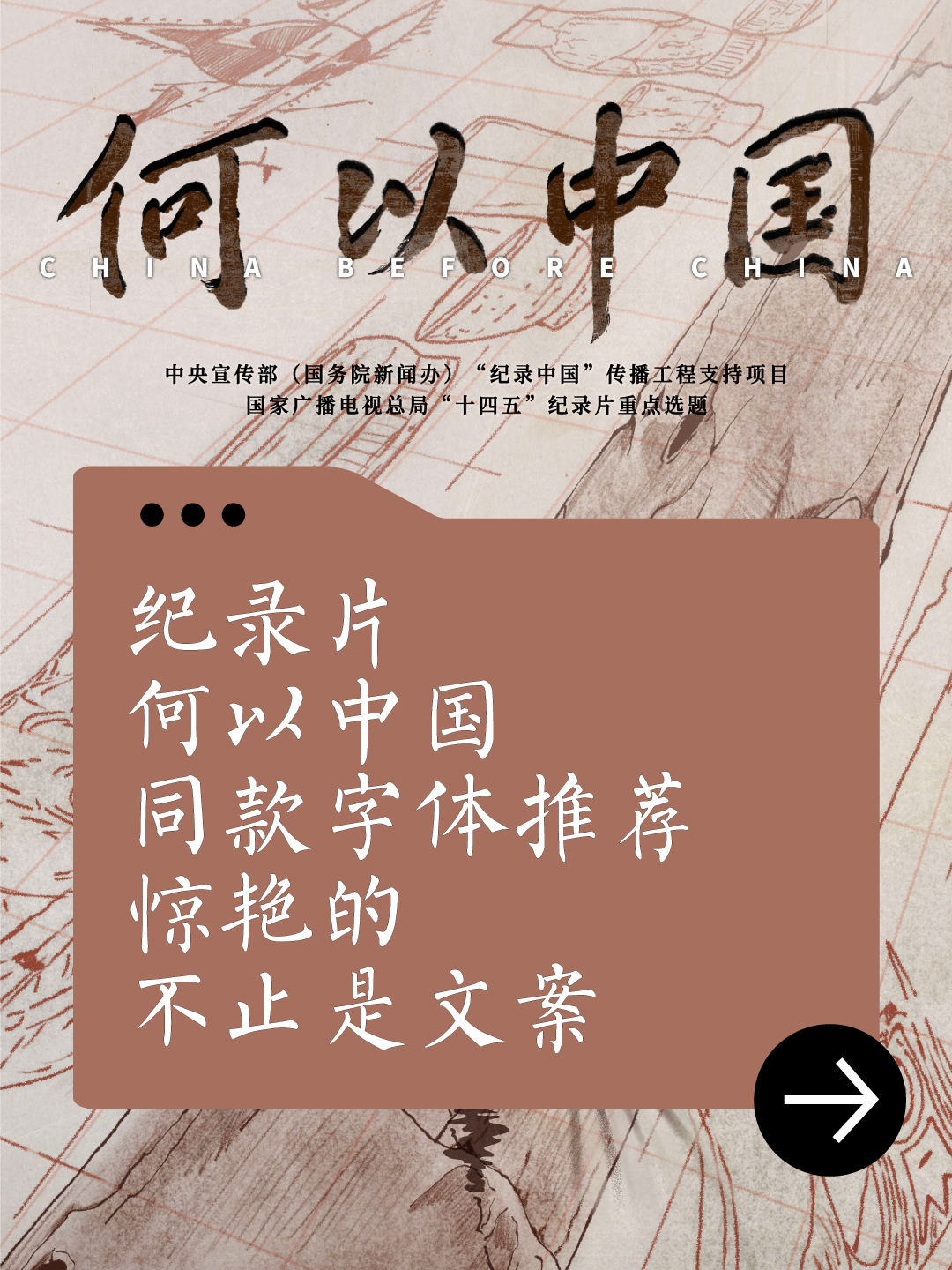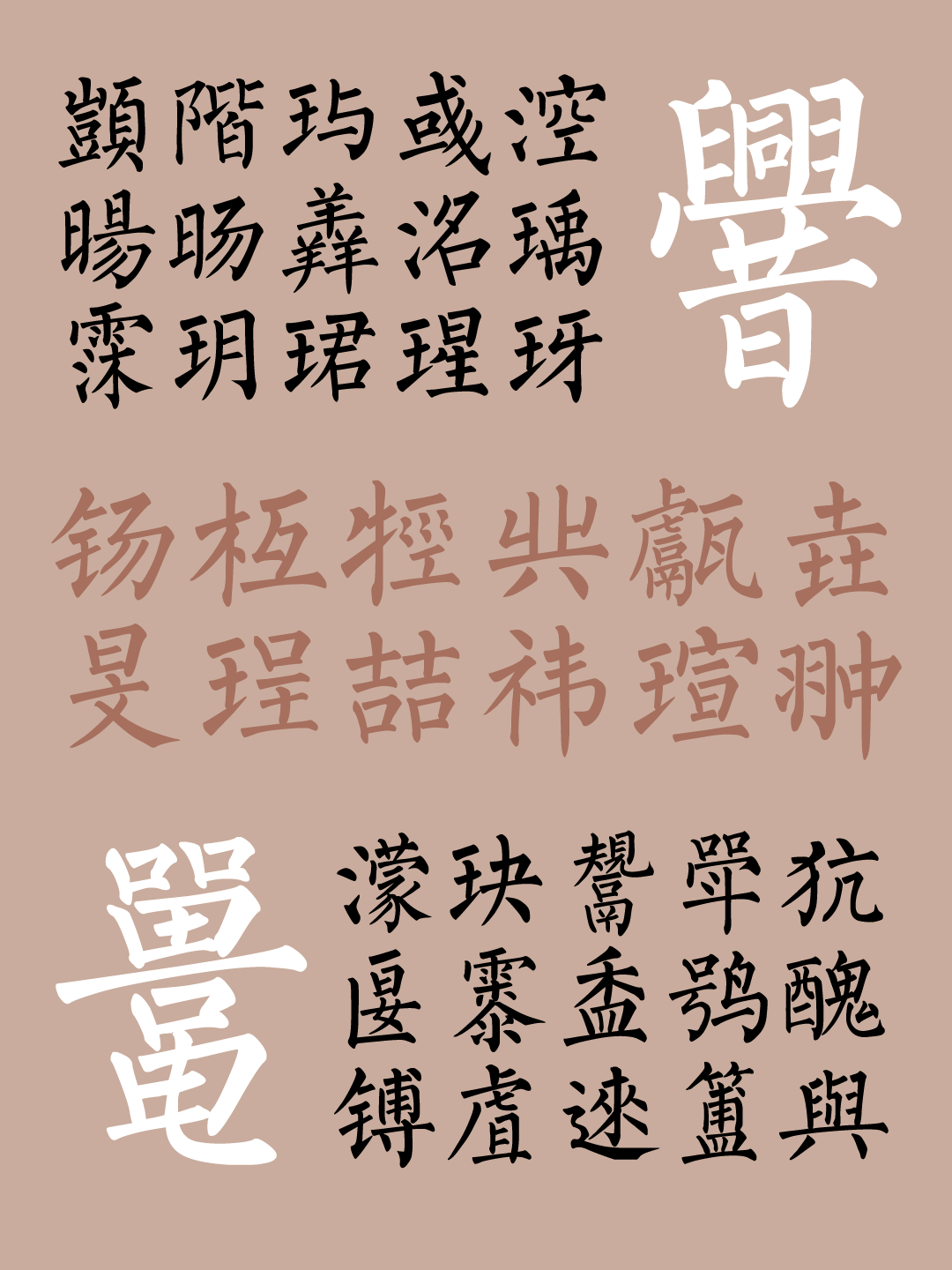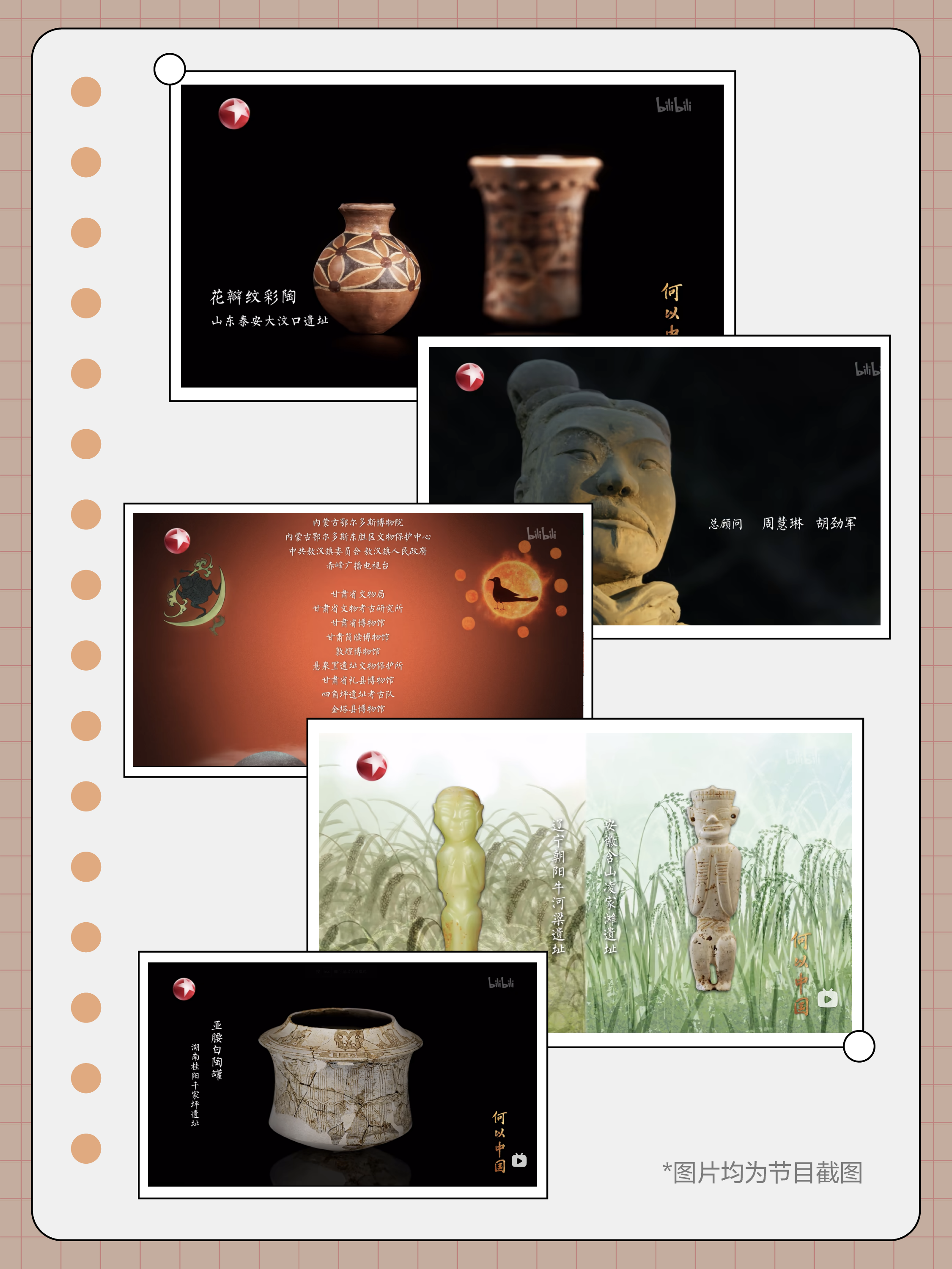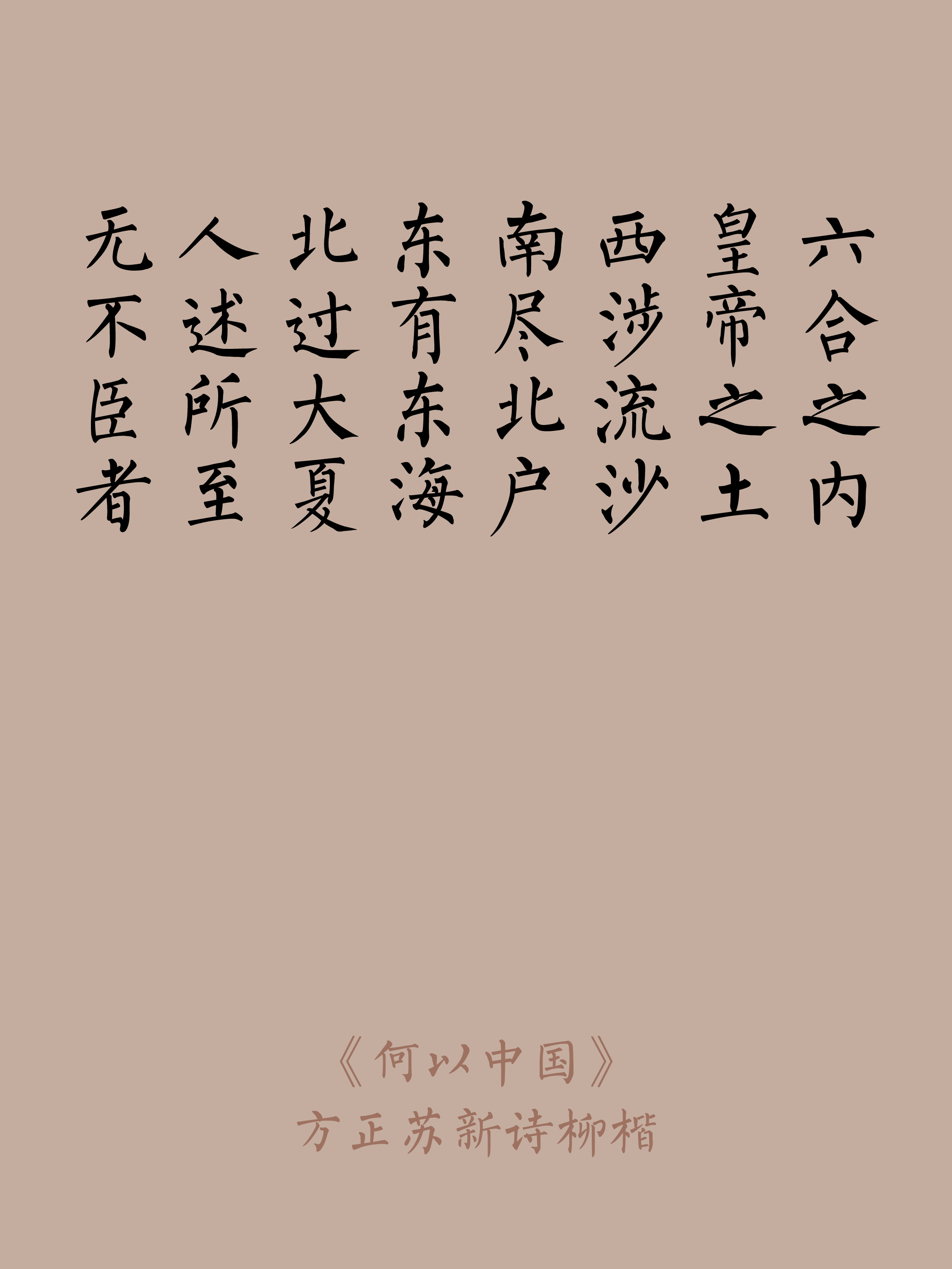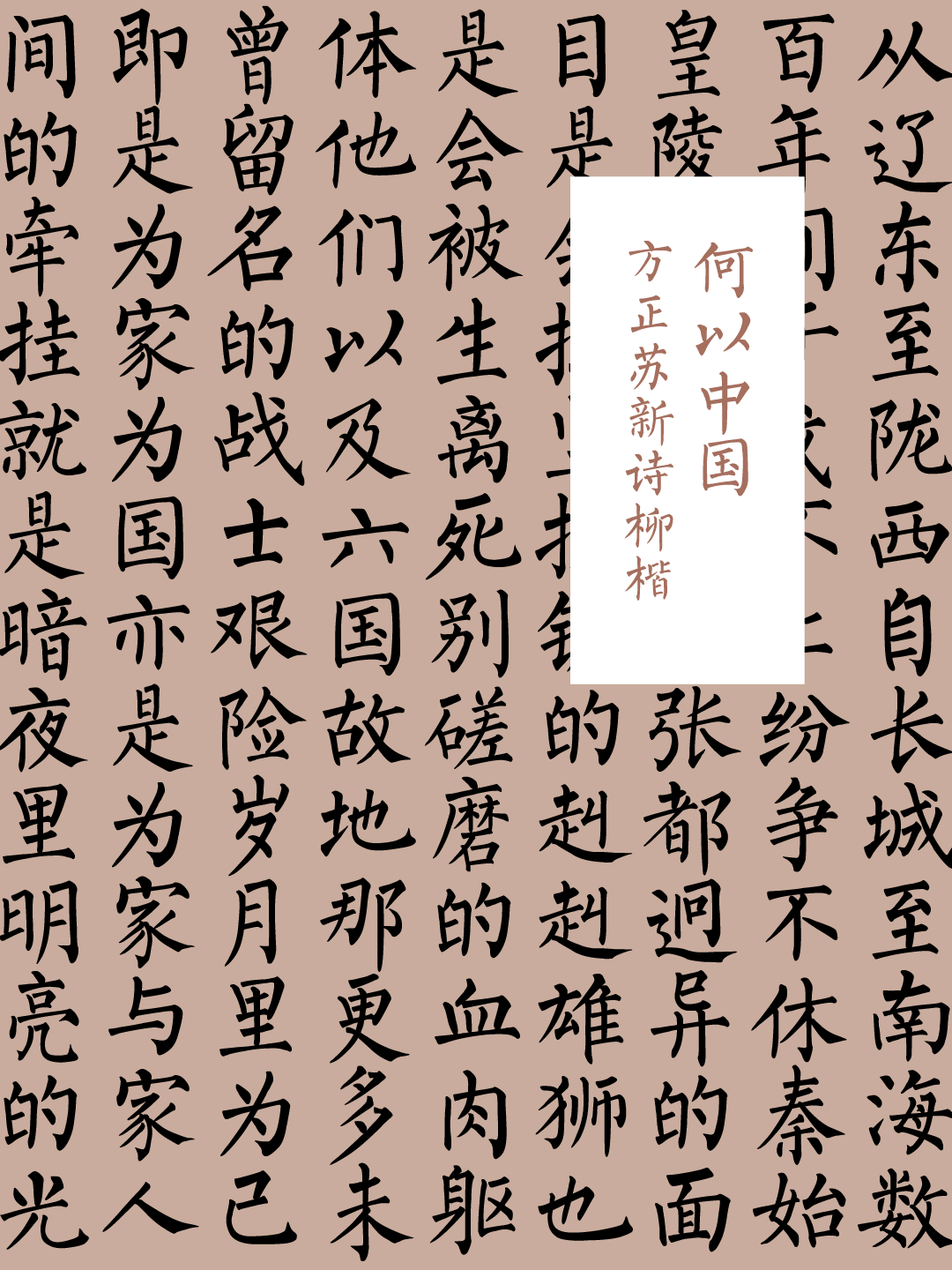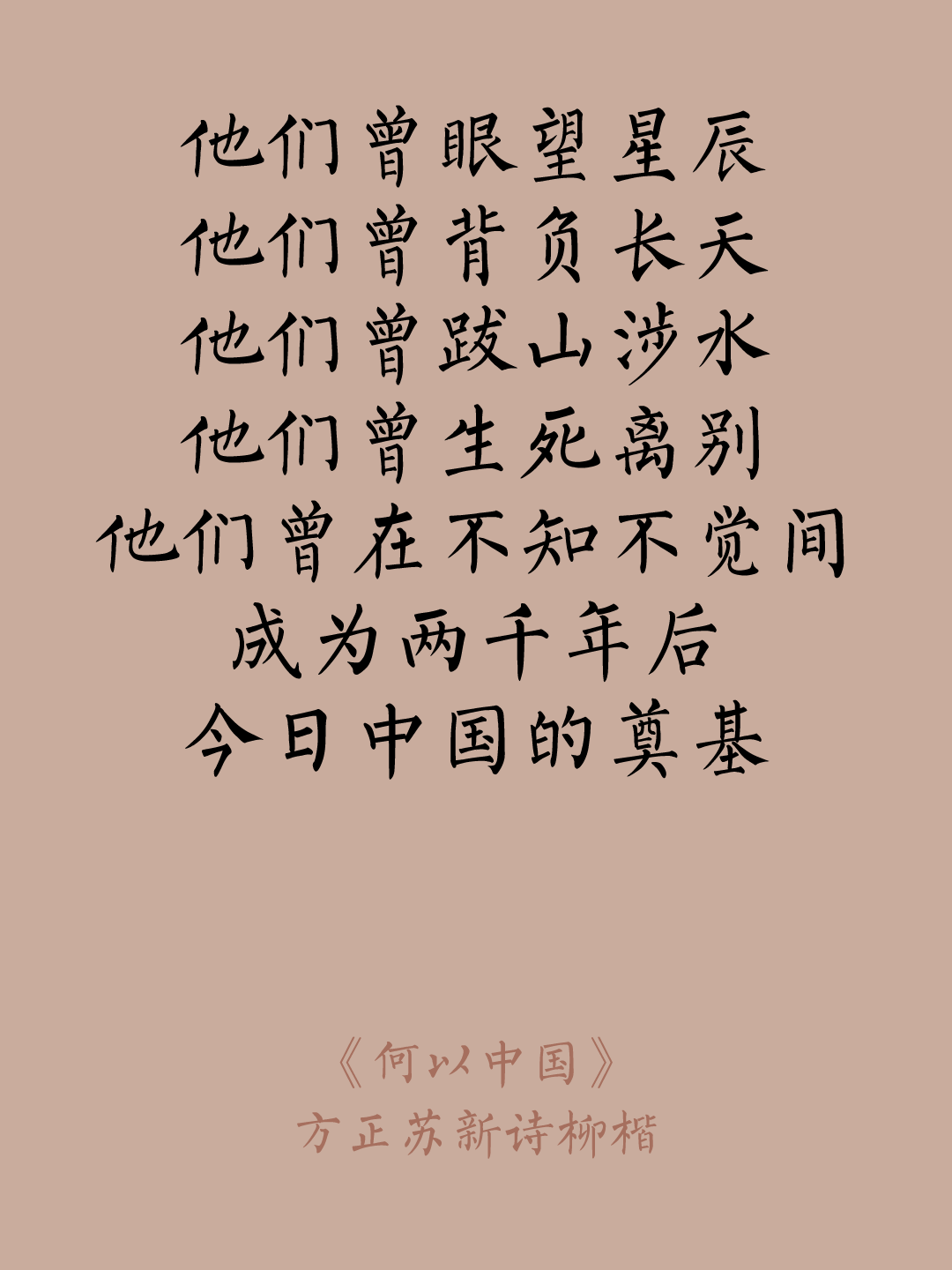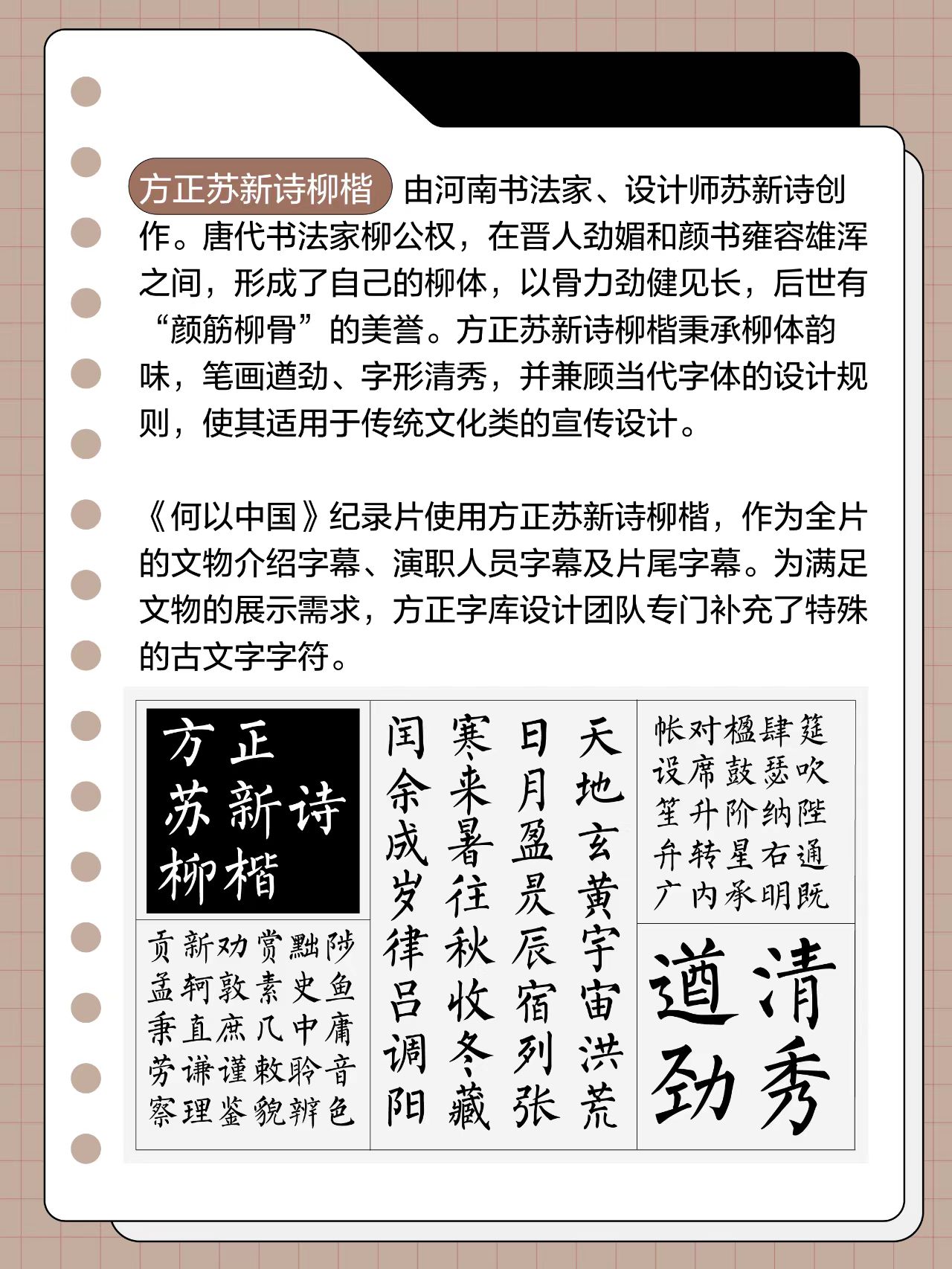
纪录片何以中国同款字体推荐,惊艳的不止是文案
大型纪录片《何以中国》是由国家文物局和上海市委宣传部指导,上海市文物局支持,SMG倾力打造的大型系列纪录片,立足于“中华文明探源工程”和“考古中国”的重大研究成果,系统性地追溯中国这个文明国家的根基、发源与早期形成和发展,全方位解码中国大地之上百万年的人类史、一万年的文化史、五千多年的文明史。
纪录片使用方正苏新诗柳楷,作为影片的文物介绍字幕、演职人员字幕及片尾字幕字体,不仅赋予了影片以历史的厚重感,更让观众在欣赏影像的同时,感受到深厚的传统文化底蕴。每一笔每一画,都仿佛在述说着千百年来的文化传承,为观众带来一场身临其境的文化盛宴。
方正苏新诗柳楷由河南书法家、设计师苏新诗创作。柳公权的书体以骨力劲健见长,后世有“颜筋柳骨”的美誉。方正苏新诗柳楷秉承柳体韵味,笔画遒劲、字形清秀,并兼顾当代字体的设计规则,使其适用于传统文化类的宣传设计。该字库字符编码为GB2312-80、GB12345-90,为满足纪录片文物展示的需求,我们专门补充了特殊的古文字字符。